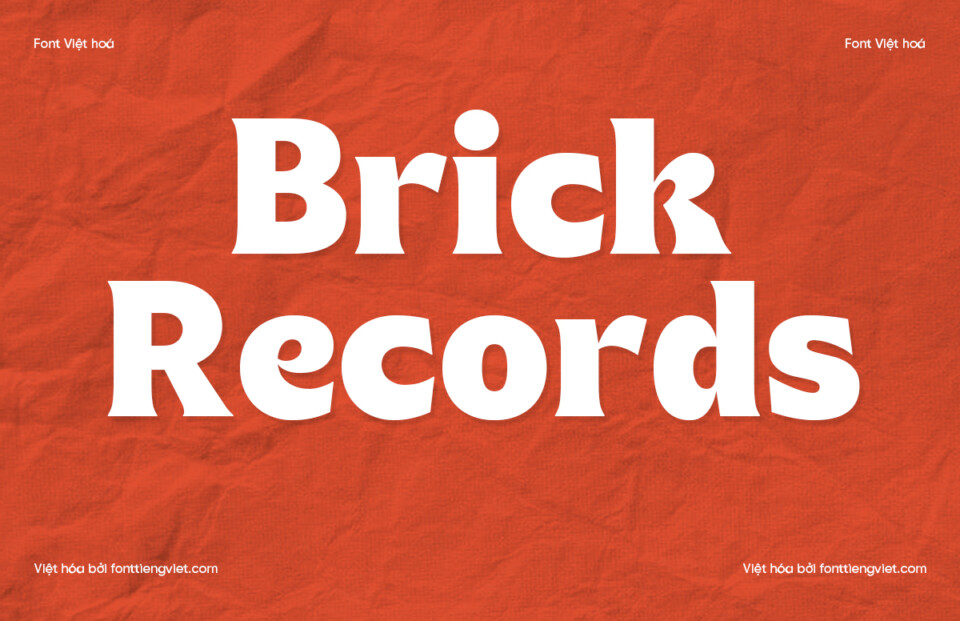
Font Việt hóa 1FTV VIP Brick Records
Tải Ngay Font Việt hóa 1FTV VIP Brick Records – Lựa Chọn Hoàn Hảo Cho Thiết Kế Sáng Tạo
Trong thế giới thiết kế đồ họa hiện đại, việc lựa chọn một bộ font chữ phù hợp đóng vai trò quyết định đến sự thành công của một tác phẩm nghệ thuật. Đặc biệt đối với cộng đồng thiết kế tại Việt Nam, nhu cầu tìm kiếm các bộ font đã được tinh chỉnh dấu tiếng Việt luôn ở mức cao. Một trong những cái tên đang thu hút sự chú ý mạnh mẽ chính là Font Việt hóa 1FTV VIP Brick Records. Đây là một bộ phông mang phong cách đô thị, lấy cảm hứng từ những viên gạch xếp chồng và các bản ghi âm cổ điển, tạo nên một diện mạo vừa cứng cáp vừa uyển chuyển. Khi bạn sử dụng Font Miễn Phí để làm phong phú thêm thư viện tài nguyên của mình, bộ font này chắc chắn sẽ mang đến một làn gió mới cho mọi dự án từ học đường đến chuyên nghiệp.
Khám phá đặc điểm nổi bật của Font Việt hóa 1FTV VIP Brick Records
Bộ Font Việt hóa 1FTV VIP Brick Records không chỉ đơn thuần là một bộ chữ cái, mà nó còn là biểu tượng của sự sáng tạo không giới hạn. Được thiết kế với các đường nét dày dặn, góc cạnh mô phỏng cấu trúc của những viên gạch trong kiến trúc, bộ font này mang lại cảm giác vững chãi và tin cậy. Tuy nhiên, các nhà thiết kế đã khéo léo lồng ghép những đường cong tinh tế để giữ cho tổng thể không bị thô cứng. Điều này giúp bộ font trở nên đa năng, phù hợp cho cả tiêu đề bài báo, poster phim hay thậm chí là các biểu ngữ tuyên truyền trong nhà trường. Việc Việt hóa tỉ mỉ giúp các dấu thanh như huyền, sắc, hỏi, ngã, nặng được đặt ở vị trí chuẩn xác, không bị đè lên chữ, đảm bảo tính thẩm mỹ cao nhất cho văn bản tiếng Việt.
Ứng dụng thực tế trong giáo dục và thiết kế sáng tạo
Đối với các bạn học sinh và giáo viên, việc sử dụng Font Việt hóa 1FTV VIP Brick Records trong các bài thuyết trình hay thiết kế báo tường sẽ giúp nội dung trở nên nổi bật và dễ tiếp cận hơn. Font chữ này có độ tương phản cao, giúp người xem dễ dàng nhận diện thông điệp ngay từ khoảng cách xa. Trong các dự án thiết kế thương hiệu hoặc làm nội dung trên mạng xã hội, 1FTV VIP Brick Records giúp tạo ra sự khác biệt độc đáo, giúp thương hiệu của bạn thoát khỏi sự rập khuôn của những font chữ hệ thống nhàm chán. Khả năng tương thích tốt trên nhiều phần mềm đồ họa phổ biến giúp quá trình làm việc trở nên mượt mà và hiệu quả hơn rất nhiều.
Hướng dẫn sử dụng Font Việt hóa 1FTV VIP Brick Records hiệu quả
Để phát huy tối đa vẻ đẹp của Font Việt hóa 1FTV VIP Brick Records, người dùng nên chú ý đến khoảng cách giữa các chữ cái (kerning). Do đặc thù là font dạng “Brick” với các khối hình học, việc điều chỉnh khoảng cách hợp lý sẽ tránh tình trạng chữ bị dính vào nhau khi in ấn. Bạn cũng có thể kết hợp bộ font này với các màu sắc tương phản mạnh như đen – vàng hoặc trắng – đỏ để tạo hiệu ứng thị giác mạnh mẽ. Hãy nhớ rằng đây là một font dạng display, vì vậy nó sẽ hoạt động tốt nhất khi được dùng cho các đoạn văn bản ngắn, tiêu đề chính hoặc các câu slogan mang tính chất khẳng định.
Lời kết về giá trị của bộ Font Việt hóa 1FTV VIP Brick Records